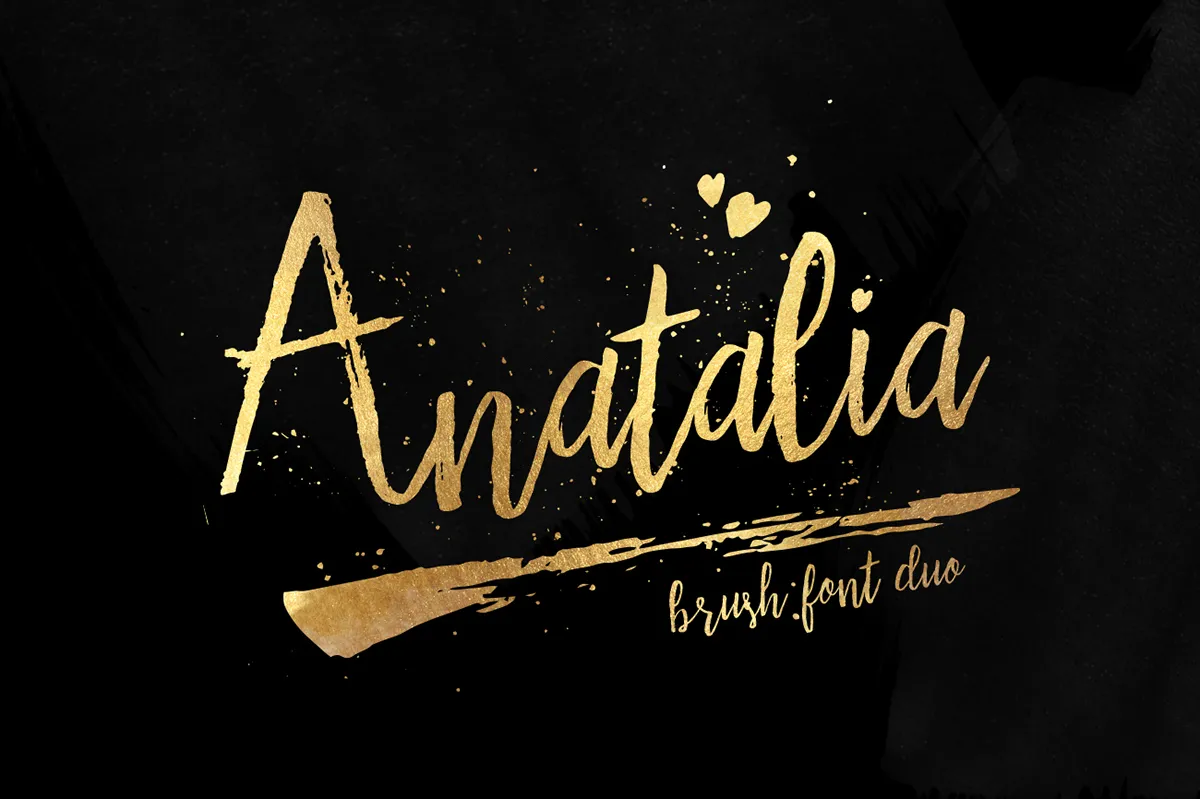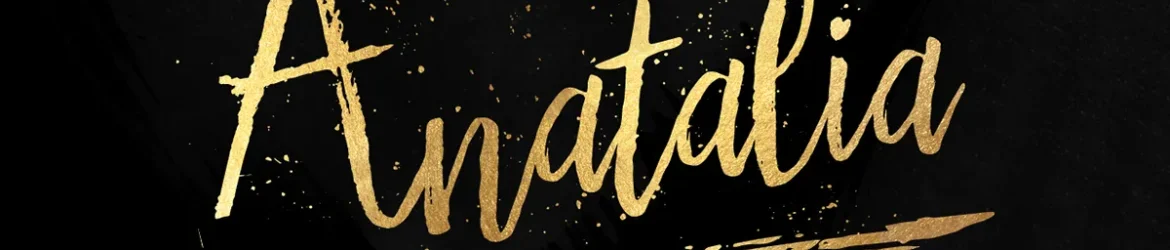
Anatalia Brush Duo Font – Download Grátis
Anatalia Brush Duo é uma fonte brush que oferece realismo e naturalidade em cada caractere. Desenvolvida pelo designer Hamilton e compartilhada pela Bowery Studio, esta fonte brilha em design de livros, capas de filmes, roupas, cartões, logomarcas e posters. Suas linhas artesanalmente desenhadas conferem um toque natural e autêntico à sua criação. A opção do OpenType adiciona mais flexibilidade aos seus projetos gráficos. Perfeita para profissionais que buscam adicionar personalidade ao seu trabalho, esta fonte é o complemento perfeito para qualquer projeto visual criativo no Brasil ou em qualquer outro lugar do mundo.